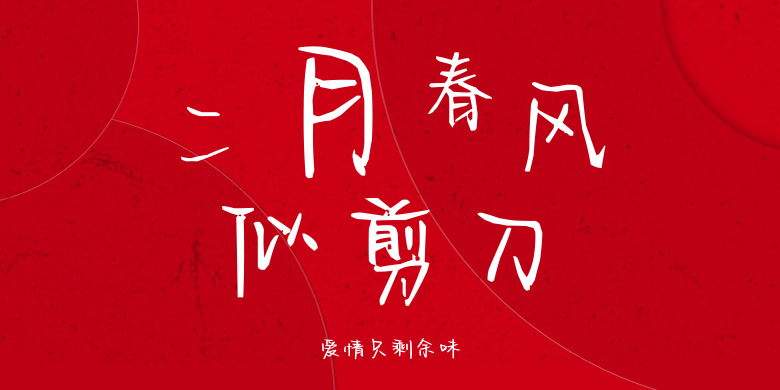
爱情只剩余味
爱情只剩余味,这款字体结构工整、笔画清晰,兼顾美观与易读性,适用于标题、正文、海报、包装、LOGO 等多种场景。字形优雅稳定,风格百搭耐看,适配日常排版与创意设计,让文字呈现更舒适、更具质感。爱情只剩余味一笔一画,皆是细节,以均衡的比例、流畅的线条打造舒适视觉体验,字形端正大气,风格简约现代。无论是商业设计、品牌宣传还是日常排版,都能轻松驾驭,让文字更有格调与力量。爱情只剩余味字体下载。